もっと知りたい!ヒラギノフォント 中の人に訊く、公式noteの舞台裏。
皆さんが、毎日何気なく目にしていると言って過言ではない「ヒラギノフォント」の文字。どこで使われているかを意識したことはありますか?
スマートフォン・タブレット端末、テレビCM・テロップ、道路標識・サイン、雑誌・書籍・ポスターなど…。
国内のありとあらゆるところで利用されている「ヒラギノフォント」は、株式会社SCREENグラフィックソリューションズ(以下、SCREEN GA)が開発・提供している書体です。
そんなヒラギノフォントのこと、もっと知りたい!と思っていた矢先、公式noteがスタートしていることに気がついた私たち編集部。
さすがヒラギノフォントの公式note。書体のイメージと同様に、丁寧で洗練されたビジュアル、かつ親しみを感じる導入で楽しく読めちゃいます。
ヒラギノフォントのPRをしている方は、どんなお方なのでしょうか…。ぜひ直接、ヒラギノフォントの魅力を訊いてみたい!
この度フォントの日(4月10日)記念企画として、夢のコラボが実現しました。
■お話を聞いた人
正木 洋介(まさき ようすけ)
株式会社SCREENグラフィックソリューションズ ビジネス統轄部 営業推進部
Webコンサルティングの会社を経て、2016年にSCREEN GAへ入社。ヒラギノフォントの広報・プロモーションを担当。
ヒラギノフォントの広報担当者に訊いてみた!
正木さんと書体、ヒラギノフォント
ー 今回はご登場いただき、ありがとうございます!正木さんは、普段どんなお仕事をされているのでしょうか?
正木 MCチーム(マーケティングコミュニケーションの略)に所属しているのですが、広報活動や展示会の実行やカタログ制作といった販促活動が含まれます。フォントとしては、ヒラギノフォント公式noteとTwitter(@screen_hiragino)の主担当者として運用しています。
2021年まではフォントの専任だったのですが、現在は印刷関連製品のMC活動と、フォント製品のMC活動を半々くらいで担当しています。
ー それは意外でした。フォントのお仕事だけではないのですね。
正木 はい、当社は主に印刷装置やワークフローのシステムが主⼒製品なんです。
片やデータしかないフォントと、片や運ぶには10トントラックが何台も必要な印刷装置…。
スケールの違いに頭の切り替えが追いつかないことも多いですが、経験豊富な先輩方に助けてもらいながら業務に取り組んでいます。
ー 幅広いお仕事に関わってらっしゃるのですね。そもそも、正木さんがフォントの業界に入ったきっかけは何だったのでしょうか?
正木 大学生の頃からぼんやりとフォントに興味が出てきて、独学でフォント制作を始めていました。卒業論文もフォントをテーマに執筆しました。
卒業後は、フォントとは関わりの薄いWebコンサルティング会社に就職したのですが、アナリストとして働く傍らで、ある勉強会に参加したことが転機になり…。
それが「和文と欧文 和文分科会 その2:自分の書きたい字を書く(以下、和文と欧文分科会)」という、1年間に渡って自分のフォントを制作する勉強会です。講師は、ヒラギノフォント含む数多くのフォントのデザインを手掛けてきた字游工房の鳥海修さんでした。
ー 鳥海さんが手がけていたとは、かなり本格的な内容ですね。どんな勉強会だったのですか?
正木 月1回の分科会でフィードバックをもらい、翌月までに修正する、というサイクルを1年間繰り返してフォントを完成させます。
1年の後半のほとんどは、試しに文字を打ってみて遠くや近く、角度を変えて見ては1-2ピクセル修正する、という作業をひたすら繰り返していたのですが、不思議と辛くはなく、少しずつ確実に整っていくことを楽しんでいました。
たった1年だけでは、フォント制作の入り口に立ったに過ぎないのですが、「書体を見る目」が確かに変わった1年でした。ここで得た経験と繋がりは代え難く、和文と欧文分科会に参加していなかったら今の仕事には就いていないと思います。
「和文と欧文分科会」終了後もプライベートでフォントの制作を続けたり、フォントのイベントを見かけては参加していたり…。フォントが好きすぎたため、心のどこかで仕事としてフォントに関わりたいという気持ちは常にありました。
ー 「フォントが好きすぎた」!そして、その想いがさらに強くなったのですね。
正木 そんな中でヒラギノの開発メンバーの求人をSNSで見かけた私は、鳥海さんがデザインしたヒラギノフォントの仕事ということもあり、飛びつくように応募したんです。縁あって2016年にヒラギノフォントの開発メンバーとして入社しました。
ー 念願のフォントのお仕事だったのですね。正木さんから見て、ヒラギノはどのような存在ですか?
正木 ヒラギノフォントのことはもちろん、入社前から存在を知っていました。鳥海さんたち字游工房がデザインした書体で、iPhoneやMacで採用されていて、綺麗で使いやすいフォントだな、という印象でした。
しかし、その後入社してヒラギノフォントのことを知れば知るほど、じっくり見れば見るほど、ヒラギノフォント、特にヒラギノ角ゴ/明朝/丸ゴの完成度の高さには驚かされました。
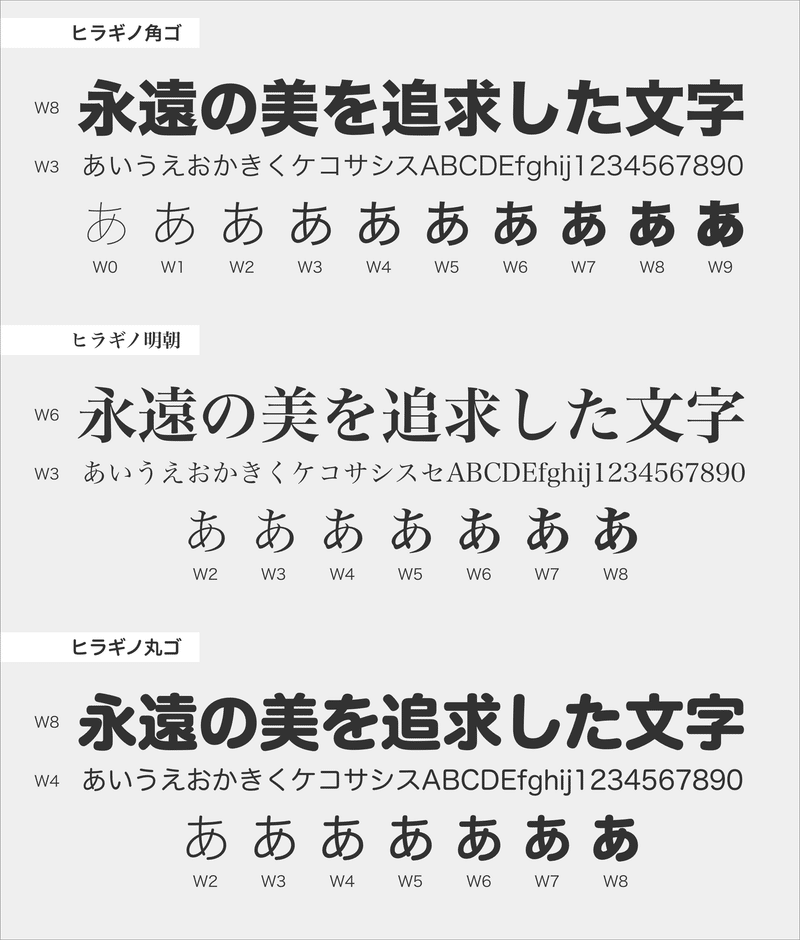
何がその高い完成度をもたらしているか、まだ全ては理解しきれてはいません。
クールでスマート、明るくクセのないベーシック書体というコンセプトや、文字同士の空間の広さが同じになるよう調整されていること、広過ぎず狭過ぎないフトコロ、高過ぎず低過ぎない重心という設計。そのコンセプトと設計を体現するために1文字1文字調整されたアウトライン…。
それらが合わさり、デザインのトレンドに左右されない普遍性、特定の印象を感じさせないフラットさをもたらしているものと思っています。
個人的な好みで言えば、ヒラギノ角ゴ オールド/ヒラギノ丸ゴ オールドがお気に入りですね。
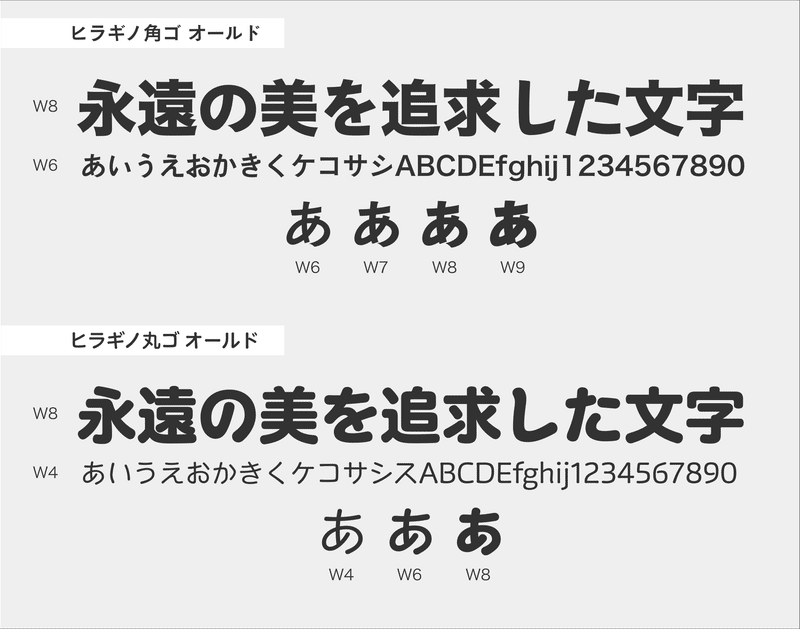
ひと癖があるけど、根っこはとても人懐っこい。そんな印象のフォントです。友達になってみたい。
ー ヒラギノが友達でいてくれるなんて、憧れます!(笑)
リスペクトでありつつ、正木さんにとって非常に大切な書体でもあるんですね。
正木 ありがたいことに、ヒラギノフォントは街のあらゆるところで見かけます。街中でヒラギノフォントが視界に入ると、すぐにカメラを取り出して写真を撮ることがライフワークになっています。
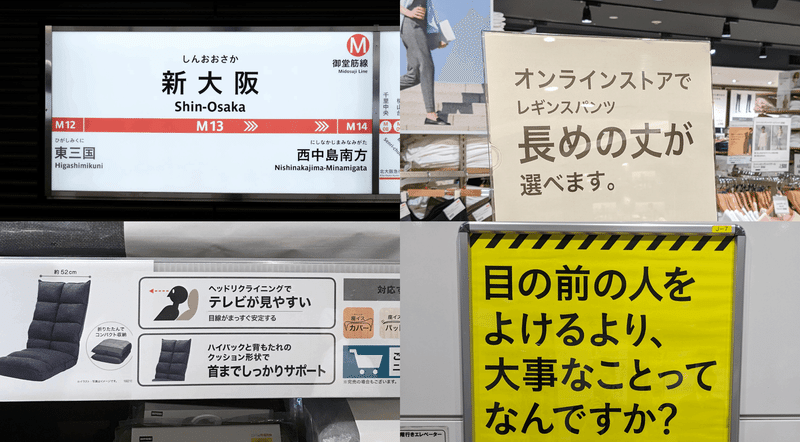
ヒラギノフォントは心の底からいいフォントだと確信しているので、このフォントたちがいつまでも使われ続けてもらえるために、出来る限りのことを日頃から考えていますね。ヒラギノフォント公式noteもその1つです。
ヒラギノをPRする日々
ー 正木さんが「ヒラギノフォント公式note」をどのようにスタートさせたのか、教えていただけますか?
正木 ヒラギノフォント公式noteは、“フォントの基本からヒラギノフォントのディープな世界まで、楽しく分かりやすいフォント情報をお届けする”メディアとして運用しています。
ヒラギノフォントは、以前から情報発信をあまりできていないことが課題だったこともあり、2021年の春頃にオウンドメディア立ち上げのプロジェクトがスタートしました。
SCREENグループ全体で見ても、これまでにオウンドメディアを運用している部門はありませんでした。ノウハウが足りていないこともあり、企画の段階から外部のパートナーとタッグを組み、打ち合わせやワークショップを何度も実施しながら少しずつ形を作りました。
企画と並行して、いろんな部署への根回しや、オウンドメディアとは?という説明を社内で繰り返しました。
思うようにプロジェクトを進められていなかった時期に、デザイナーの今市さん(@ ima_collection)から素晴らしいデザイン案を受け取って、モチベーションが急回復したことも記憶に残っています。
そして2021年の11月に初めての記事を公開し、運用が開始。現在まで1年半近くが経過し、ようやくオウンドメディアとSNSを運用するスケジュール感覚が体に馴染んできました。
記事の企画は、大体3ヶ月に1度で企画会議を実施しています。
まずいい企画が思いつくまで一人で考えてみて、その後編集メンバーや筆者の方と打ち合わせを行い、記事の企画を深めていきます。
一方で、今でも何をKPIにすべきなのか、どの程度リソースをかけるのか。度々議論を繰り返しています。
今後もあらゆるバランスをとりながら、ヒラギノフォント公式noteを大きくしていきたいです。
ー note記事を制作する上で、大切にしていることを教えてください。
正木 いつも意識しているのは、一般企業に勤めているフォントやデザインに関わる方・興味がある方にも読んでいただきたいということです。
デザイナーの方じゃなくても楽しめるよう、テクニカルになりすぎない読み物となるように企画を考えています。
正木さんセレクト!これまでのおすすめnote記事3選
(1)その中国語の案内文、フォントがツギハギになっているかも?〈エリックの多言語文字散歩〉
観光客向けの看板、よく見たらフォントがばらばら…?多言語の案内を作るときに気をつけたいポイントについて解説されています。
(2)デザインコンサルファームMIMIGURIと考えるブランディングとコーポレートフォント、フォントの未来
MIMIGURI さんに「コーポレートフォント」というキーワードを中心に、企業とデザインの関係を紐解いていく、CI/VIに関わる方は必見のインタビューです。全3回と大ボリュームなので、お時間があるときにじっくり読むのがおすすめです。
(3)表情豊かで、どこか懐かしい新書体「ヒラギノ丸ゴ オールド」を詳しくご紹介
2022年のMorisawa Fonts・MORISAWA PASSPORT新書体としてもリリースされた「ヒラギノ丸ゴ オールド」が、制作の経緯やデザイナーインタビューを交えて紹介されています。当初はレタリングで書き下ろされたというエピソードや、その後の開発で施された細やかな工夫の数々が読めちゃいます!
正木 様々な事情で、立ち上げ以降スローな更新頻度になってしまっていたのですが、これからはもう少し頻度を上げて記事をお届けする予定です。今も、執筆済みあるいは執筆予定の記事で、楽しんでもらえる自信がある記事や企画がいくつも待機しています。
そして今回のコラボを通じて、正木さんのように、書体のことを支えながら大切に伝えていく人の存在は、フォントの世界には絶対に不可欠ということも再認識できました。